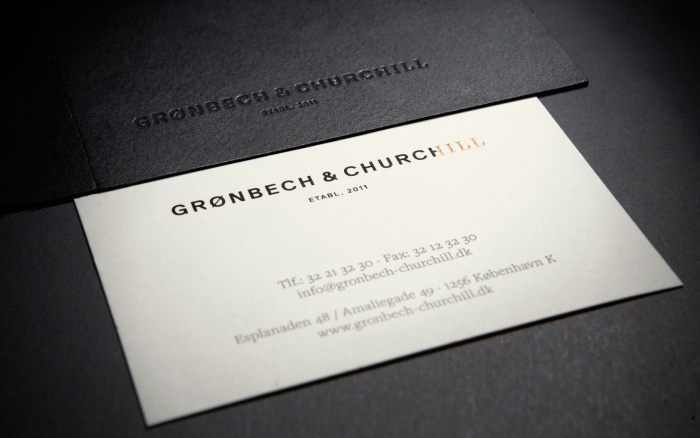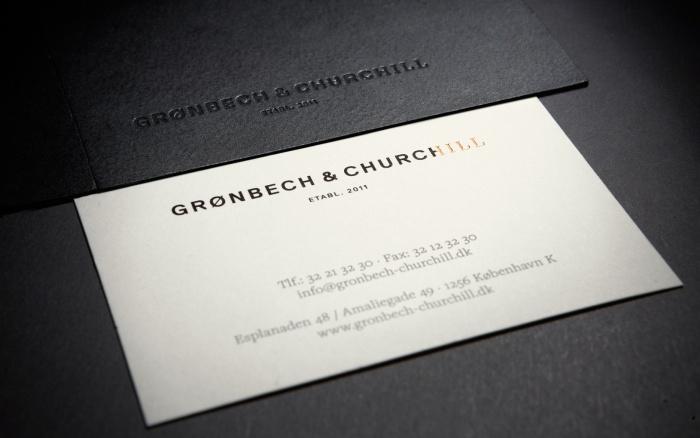
Wer kennt diese Schriften?
ausgehend von den abbildungen hier dürfte die antiqua jene sein: freight text. die sans – hier größer – sieht modifiziert aus, aber angesichts der vielzahl an schriften in diesem genre gibt es sie vielleicht auch so zu kaufen. ohne diese abgeschrägten ecken ähnlich ist fakt von ourtype.
Ich frag’ mich was der »Gag« im Logo darstellen soll. Abgegessene Knochen?
Das ist ein Hinweis darauf, wie du dich nach dem Essen fühlst. ILL.